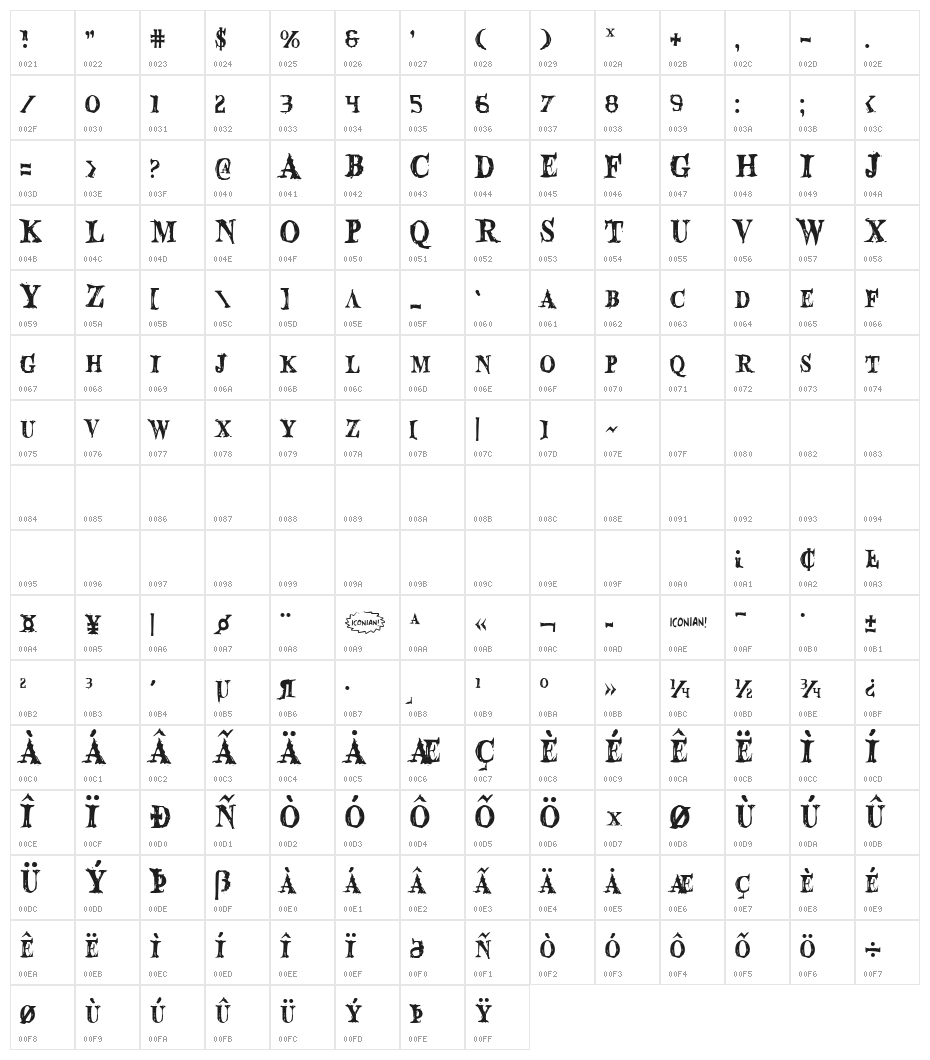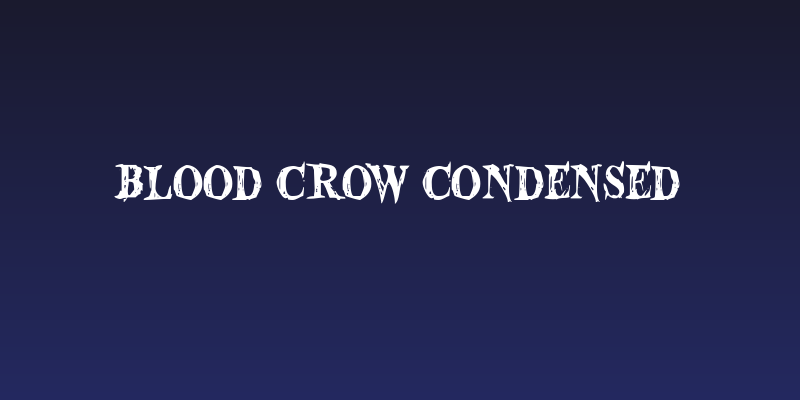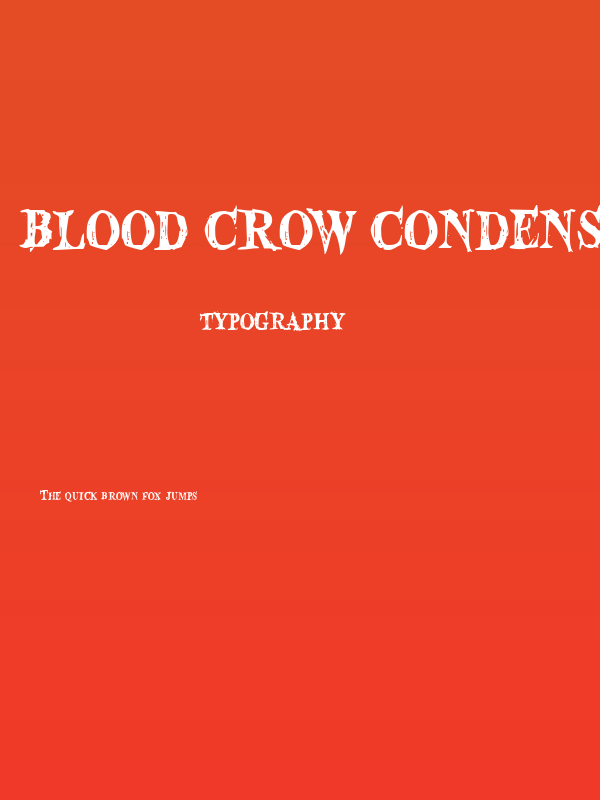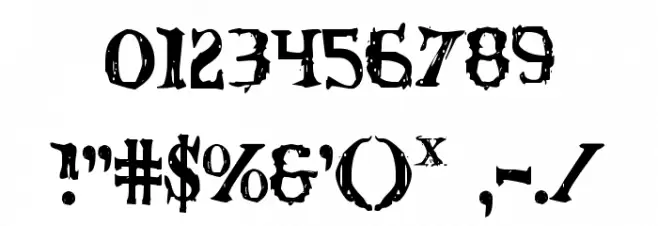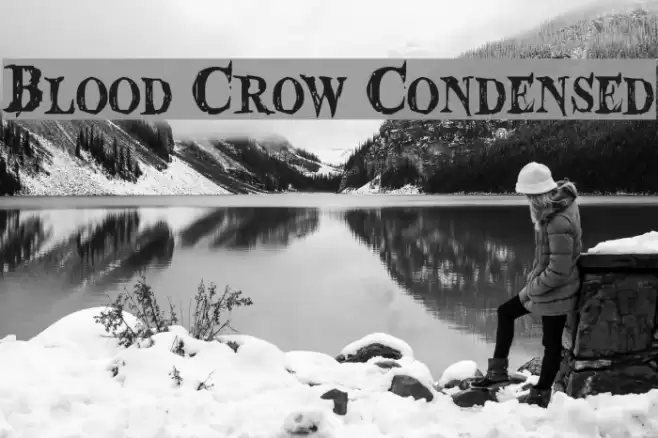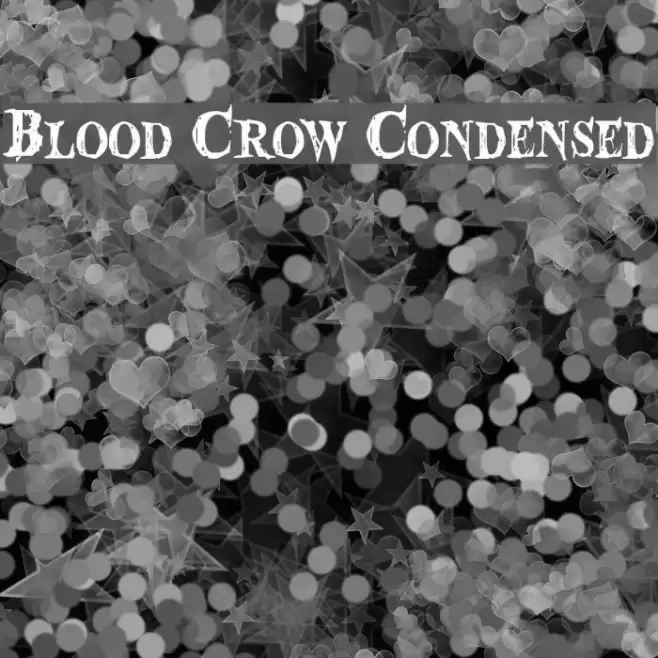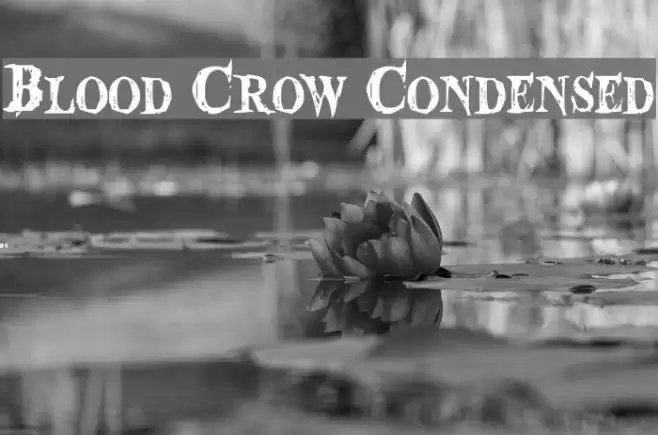
Blood Crow Condensed Font
| Estilo general | Grunge, Edgy, Distressed |
| Proyectos propuestos | Ideal for music album covers, horror movie posters, edgy branding, and graphic novels. |